コピペできない“木”03「テンの4画目」
4画目をテンにする「木」があるとシリーズ初回記事で紹介しましたが、このテンは文字に応じて時には他の筆画より大胆と思える程の調整が入ります。木偏などでは右側にくる要素とぶつかりやすいので、小さくしたり起筆の位置を下げたりしてこれを回避しています。どの文字でも小さく統一すれば良いということはなく、空間に余裕があるときは理想的な大きさと位置に整えます。文字全体から見ると小さなテンかもしれませんが、これがないと違う文字になってしまう可能性もあり、特に本文用にも使うようなフォントならテンを省略することはありません。
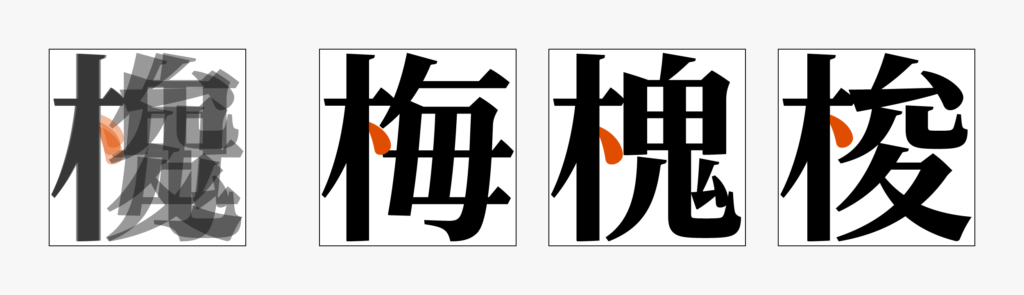
ちなみに4画目がハライだと左右ハライを同じくらいの長さに見せたい場合が多いのですが、全く同じ高さにするのではなく右はらいを若干上げることで自然に見えるようにする調整がよく行われます。